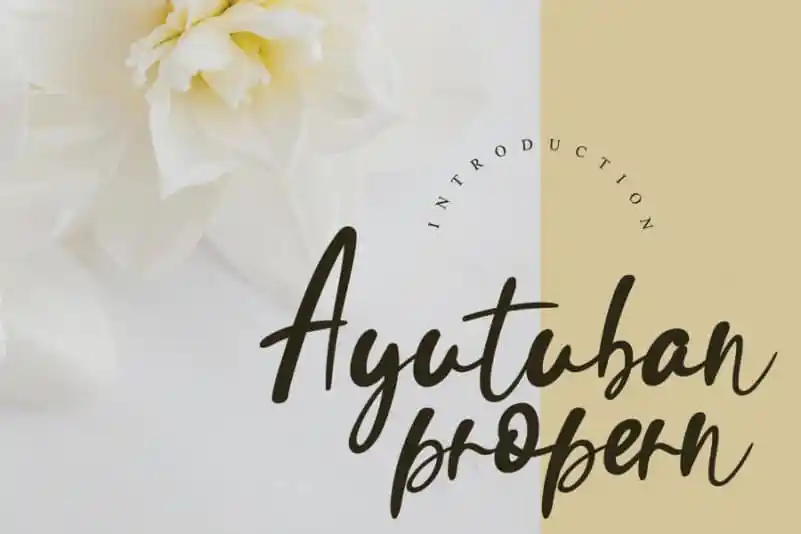
Ayutuban Handwritten Font – Download Grátis
A Ayutuban Handwritten Font é uma elegante tipografia escrita a mão que flui suavemente, criada com auxílio de um lindo penhoar. Seu estilo clássico e influência do calligrafia são mantidos enquanto ele se sente contemporâneo e atual. Esta fonte será um amor para qualquer projeto onde você deseja dar vida à sua produção. Sua calma e sofisticação irão transformar qualquer texto em algo único e emocionante, tornando seus trabalhos mais atraentes e autênticos. Descubra o poder de uma tipografia escrita a mão neste fonte única da Ayutuban Handwritten Font.